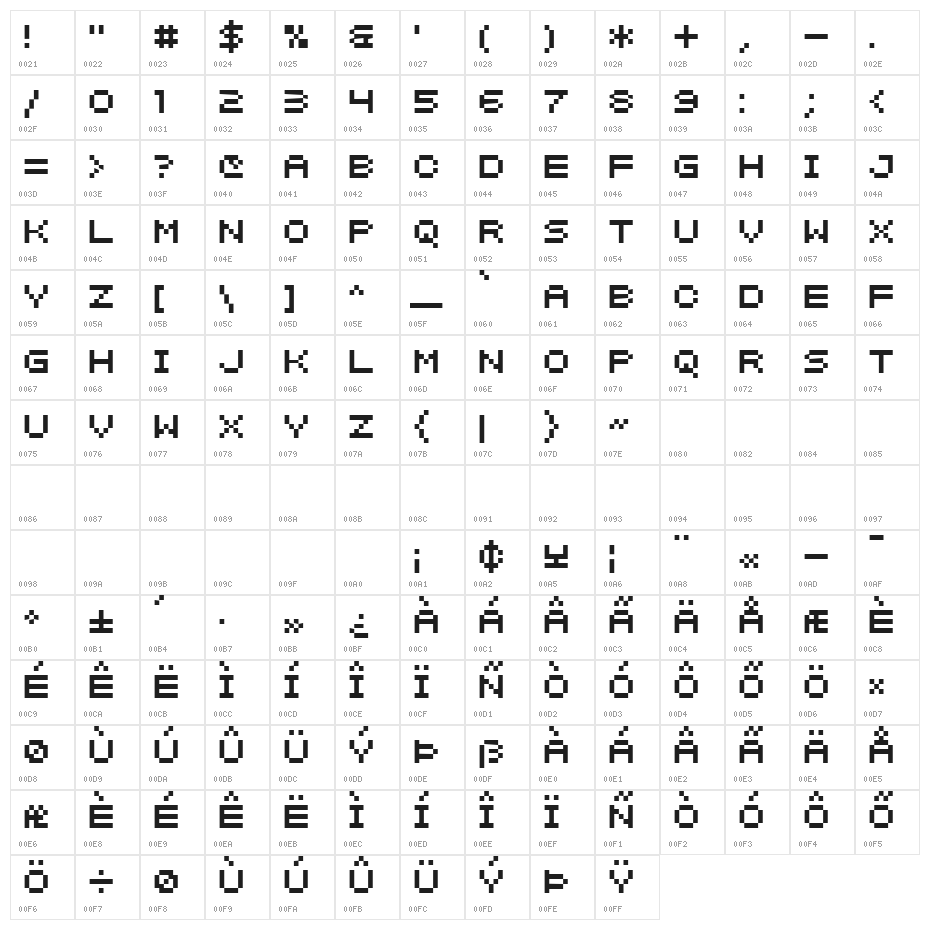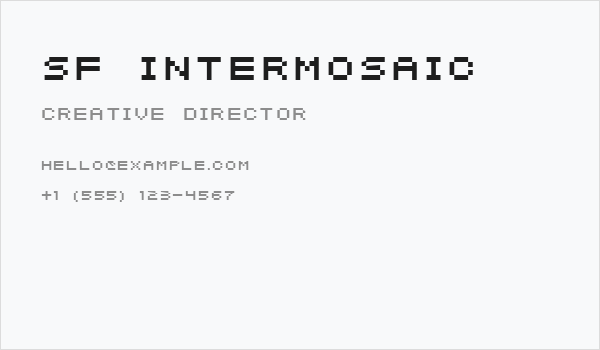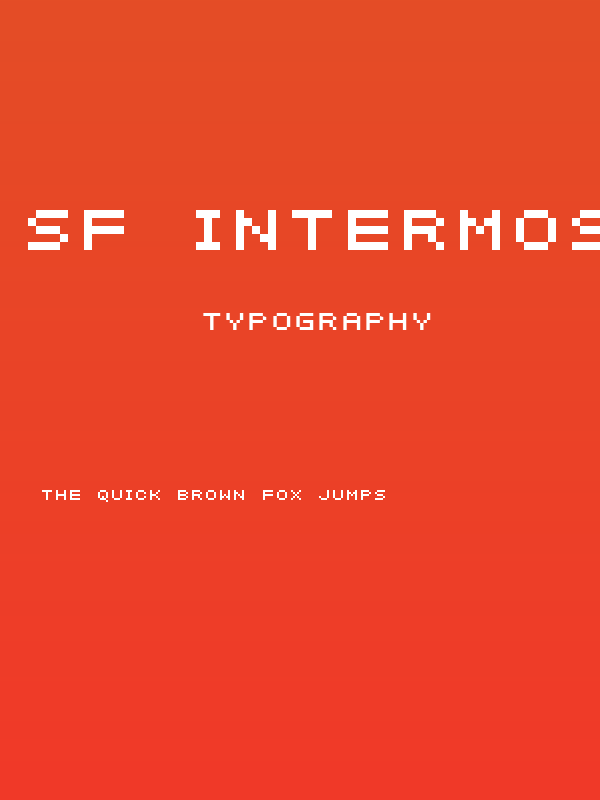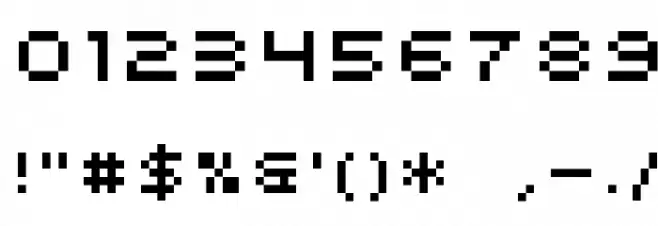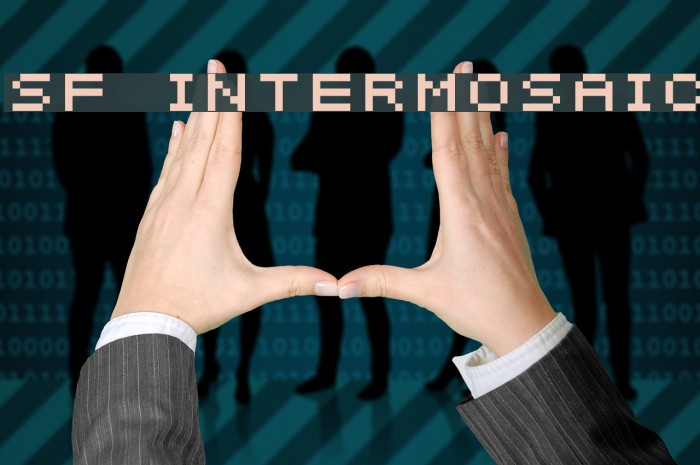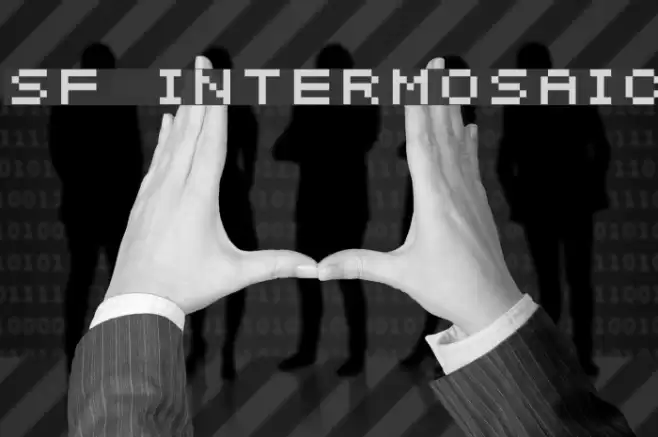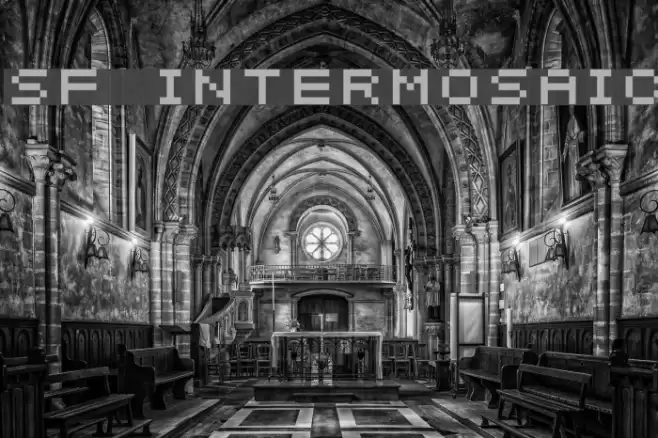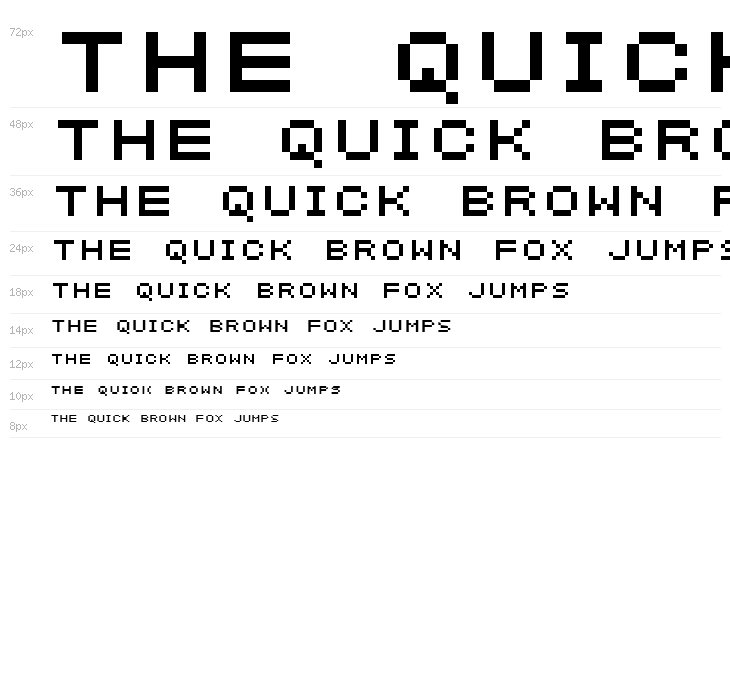
SF Intermosaic Font
| カテゴリ | Pixel |
| 全体的なスタイル | Retro, Digital |
| 用途 | Headlines, Logos, Digital displays |
| おすすめプロジェクト | Ideal for retro video game designs, digital art projects, tech-themed branding, or any project requiring a nostalgic digital look. |